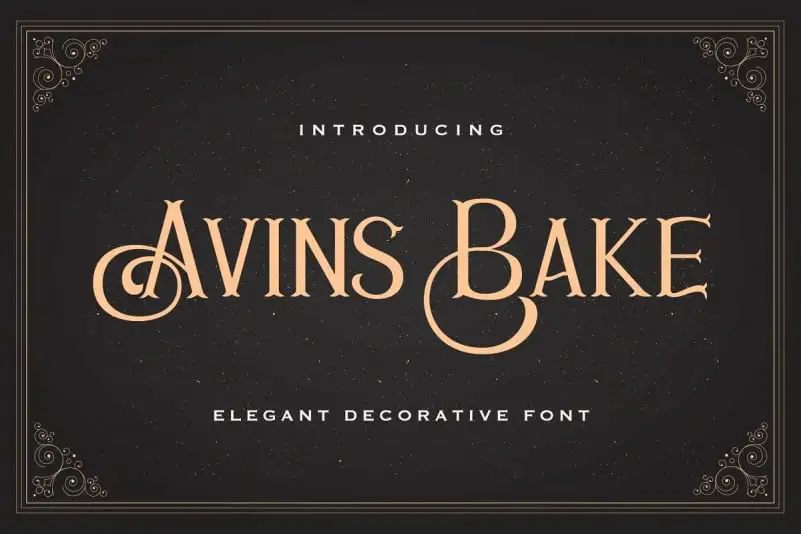
Avins Bake Display Font é uma elegante e clássica fonte capuchada que traz à tona um estilo atraente para projetos digitais. Desenvolvida pelo designer de fontes StringLabs, Avins Bake está perfeitamente adaptada para criar qualquer projeto vintage, como logotipos, embalagens de produto, convites, citações, camisetas, etiquetas, cartões de nome, selos e panfletos. Seja você um designer ou um amante do design, Avins Bake é uma ótima escolha para dar vida a projetos vintage em qualquer formato digital ou impresso. Assim que receber sua fonte, você terá à disposição uma ferramenta poderosa para criar designs clássicos e impecáveis, tornando o processo de criação mais leve e mais divertido do que nunca.